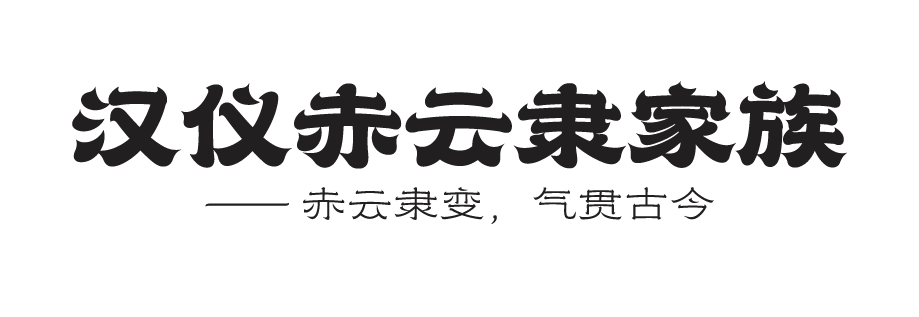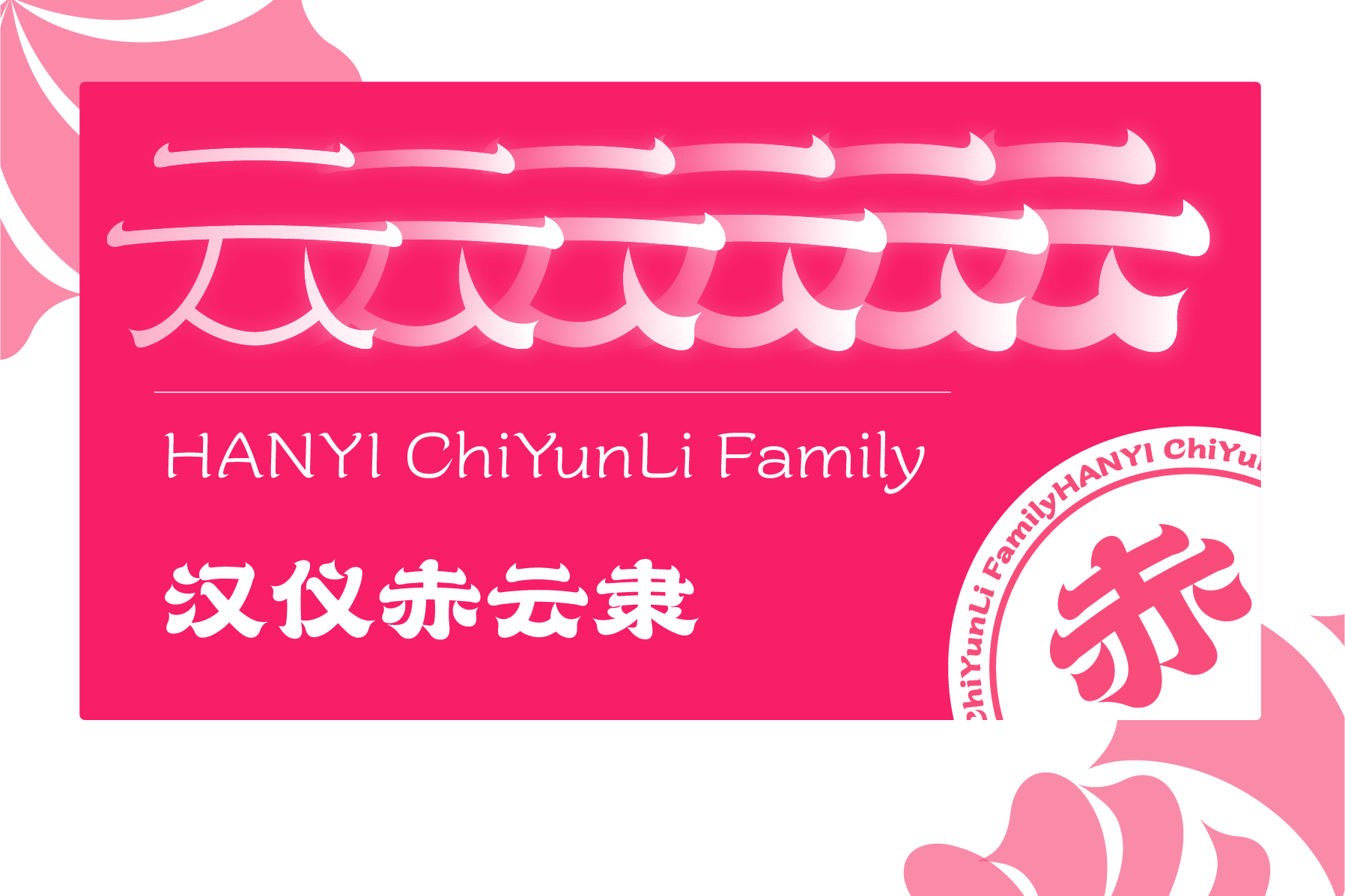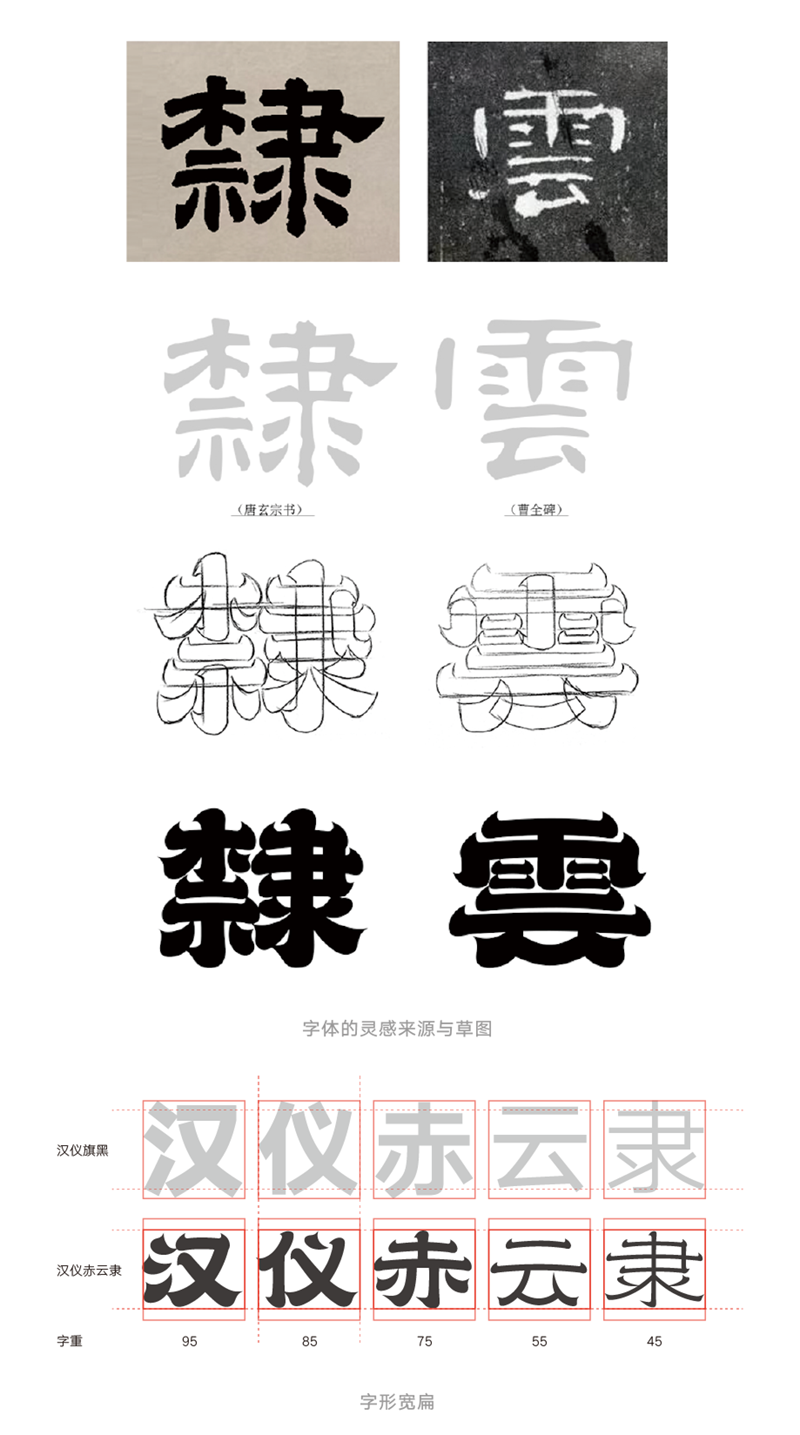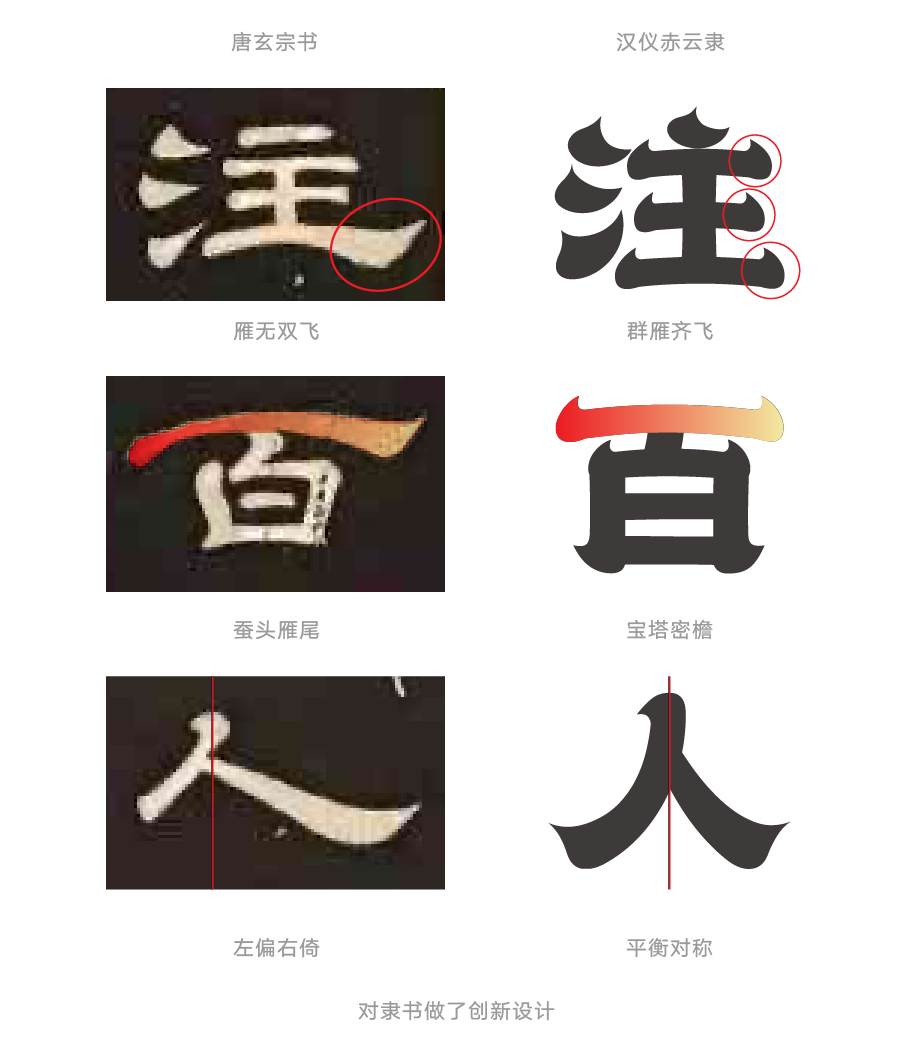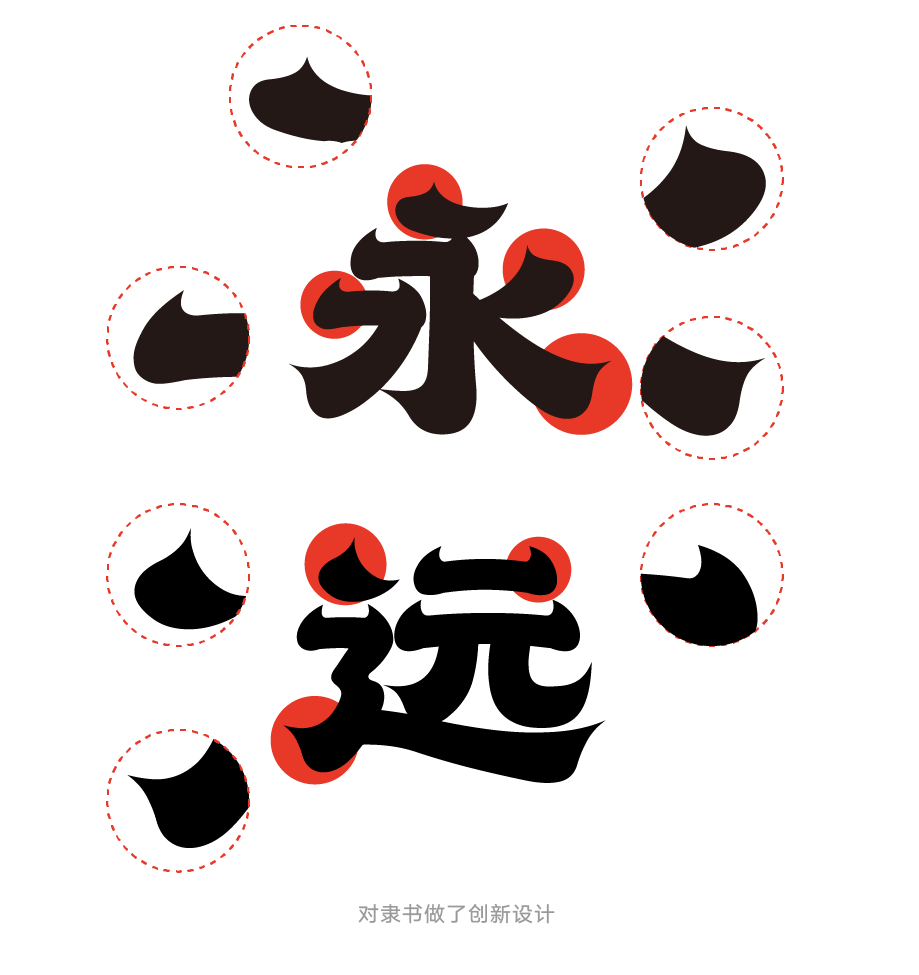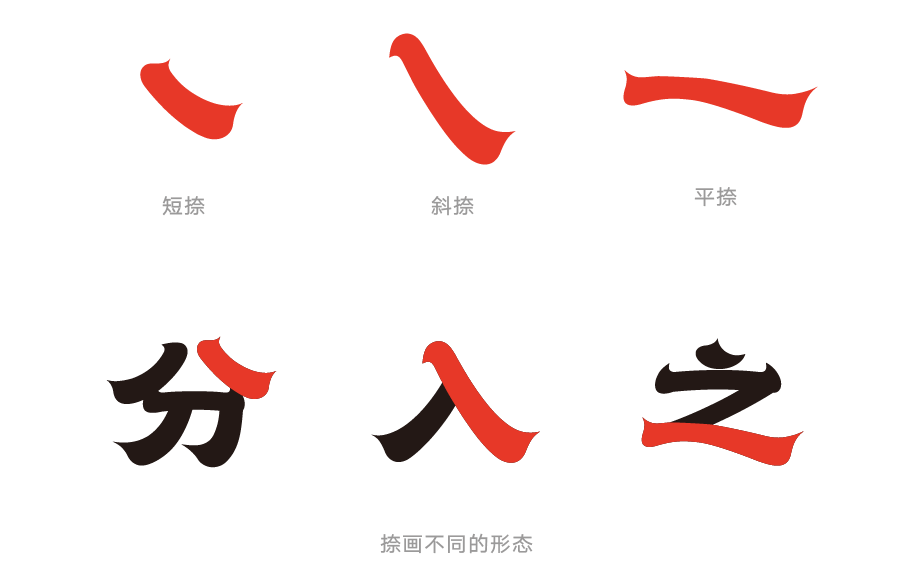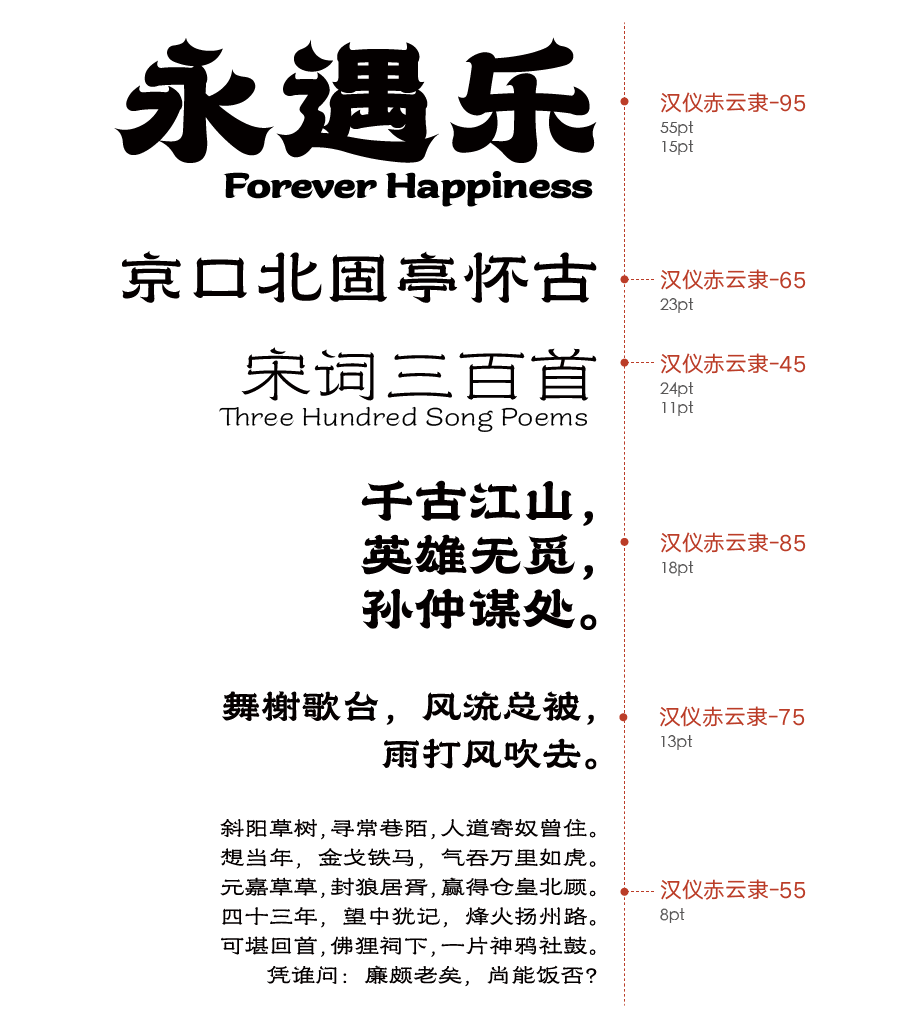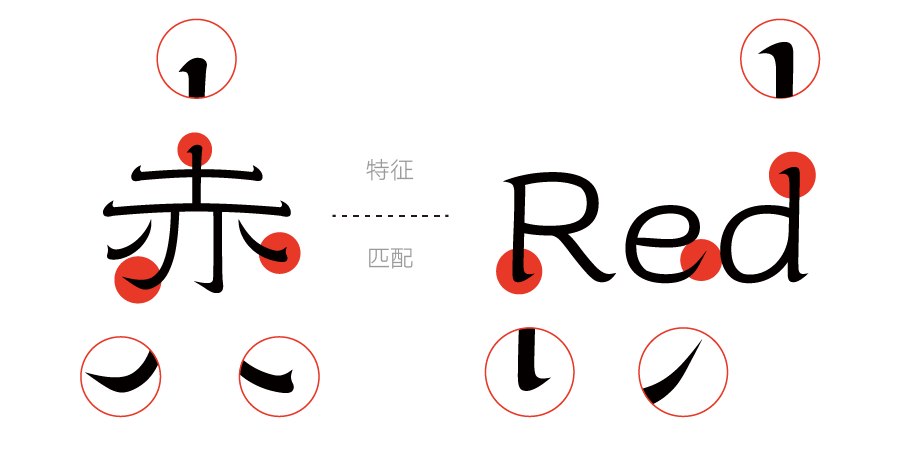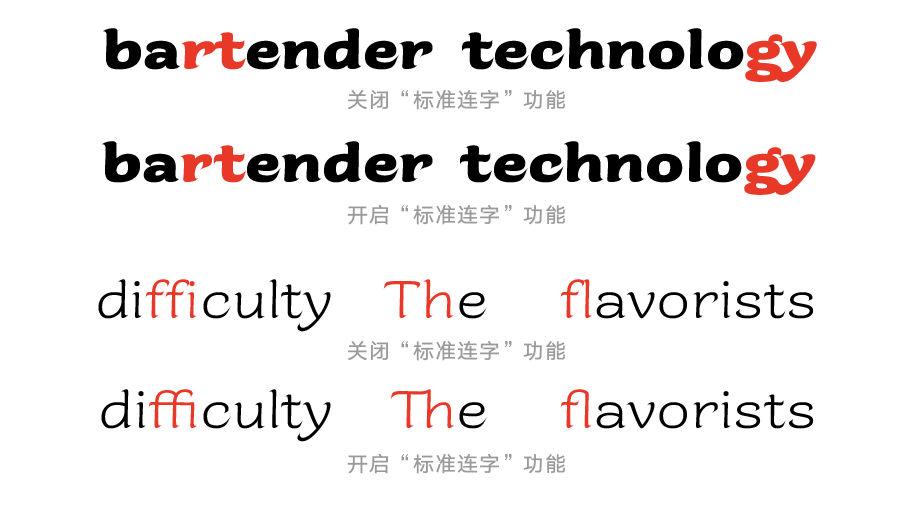
汉仪赤云隶字体介绍,一款专为国潮而生的字体,还有家族系列
汉仪赤云隶 | 赤云隶变,气贯古今
“汉仪赤云隶”是由知名设计师行行珂与汉仪字库合作打造的一款带有隶书韵味的设计字体。这款字体运用现代设计语言,在隶书的基础上改造创新,给予了传统字体新的生命力。它曾入选:“Award360°年度设计100”、“DFA设计奖”等多种设计奖项,作品样张被收录进《第十四届亚太设计年鉴》、《Design 360°n.84 #特刊#》和《字赋不凡2》等设计杂志中。
“汉仪赤云隶”造型风格既中式又新潮,它有着火焰般的热情与赤诚,从云般的厚重与气势,给人带来喜庆、祥瑞的氛围,是一款广泛适用于国风风潮环境的优质标题字体。
“汉仪赤云隶”目前已成功实现字体家族化,该字体家族总共包含6个字重:45/55/65/75/85/95,更多的字重,可以满足不同视觉层级的需求,为设计师排版提供更丰富的解决方案。
汉仪赤云隶 | 结字古中带新
“汉仪赤云隶”在结字方面从碑帖中寻找灵感,参考了唐玄宗书法与《曹全碑》的隶书风格,保留了传统隶书的诸多造型特点:字形宽扁,重心一致,字取横势,笔触方中带圆,笔画布局均衡匀称。
为平衡传统中式风格与现代时尚有设计感风格之间的矛盾,“汉仪赤云隶”从设计角度对传统隶书进行了大胆地创新。它打破了隶书雁无双飞、蚕不二设的传统,将一个字中的仅有的大波磔,分散转化成数个小“火焰”,视觉上比传统隶书更加繁复缤纷。字形间架结构被设计的更加对称、平衡,符合当下文字审美。
汉仪赤云隶 | 笔端张扬外放
“汉仪赤云隶” 在古隶书温润的基础上融入张扬外放的笔触,在起、收笔处的笔画设计上强化了笔锋造型,具有一定装饰性,如同燃烧的火苗一样,在这个年轻的时代迸发出独特的张力和韵味。
汉仪赤云隶 | 曲线灵活多变
“汉仪赤云隶”的笔画在字体不同的位置有不同的状态及表达。以“捺”笔画为例,按字形特点共分为“短捺”、“斜捺”和“平捺”。“短捺”的捺身较短促;“斜捺”头细尾粗,比较陡峭;“平捺”则一波三折,形似波浪。
汉仪赤云隶 | 字重风格变化
“汉仪赤云隶”新增了多个字重,更加丰富了字体的表现能力。95号字重笔画浑厚有力、气势宏大,行笔流畅有力度,线条饱满有弹性,气氛喜庆活泼。45号字重在字面效果上强化了碑刻感,曲线纤细而有弹性,笔画起收如铁画银钩般锐利灵动。
“汉仪赤云隶”字体独特的气质决定了它更适合用在海报招贴、logo等标题性质的场合。95和35号字重适合作为标题放大展示以彰显细节、75和85号字重适合排小标题,而55和65号字重适合排一些较短的正文内容。
汉仪赤云隶 | 中西文匹配
“汉仪赤云隶”的西文设计同样参照了传统的英文书法,运用了Upright italic(竖直意大利体)的骨架来对应中文隶书这样的书写感。汉仪赤云隶的西文有着明显的笔画走向。
“汉仪赤云隶”的西文既留有传统英文书法的结构又参照了中文笔画的特点。这使得汉仪赤云隶的中西文在历史文化和现代设计上都有着极高的匹配度。
“汉仪赤云隶”西文部分制作了大量合字,以此解决西文中某些字母相邻时会撞在一起的问题。(须在Opentype面板开启标准连字功能)
汉仪赤云隶 | 展示样张